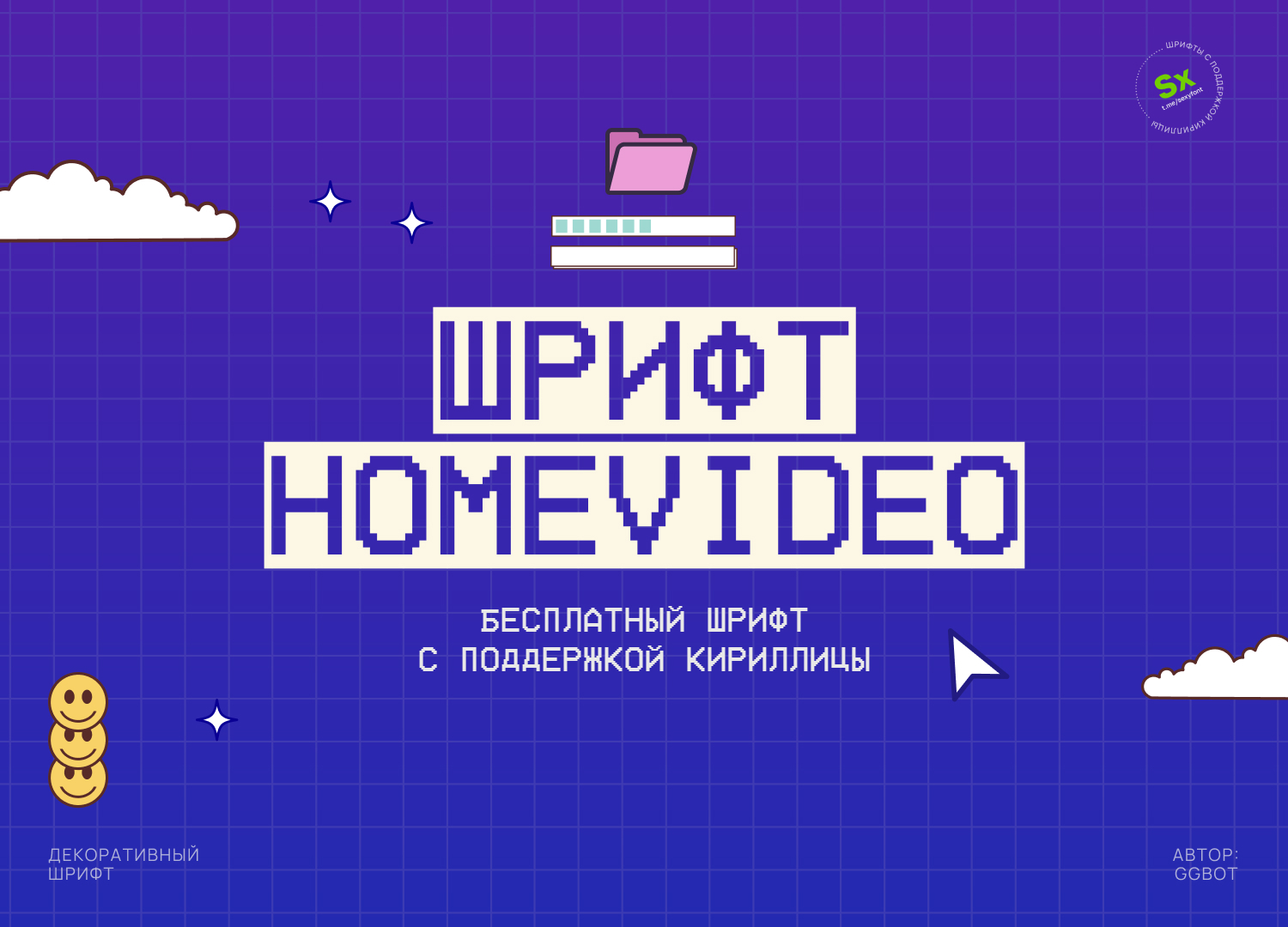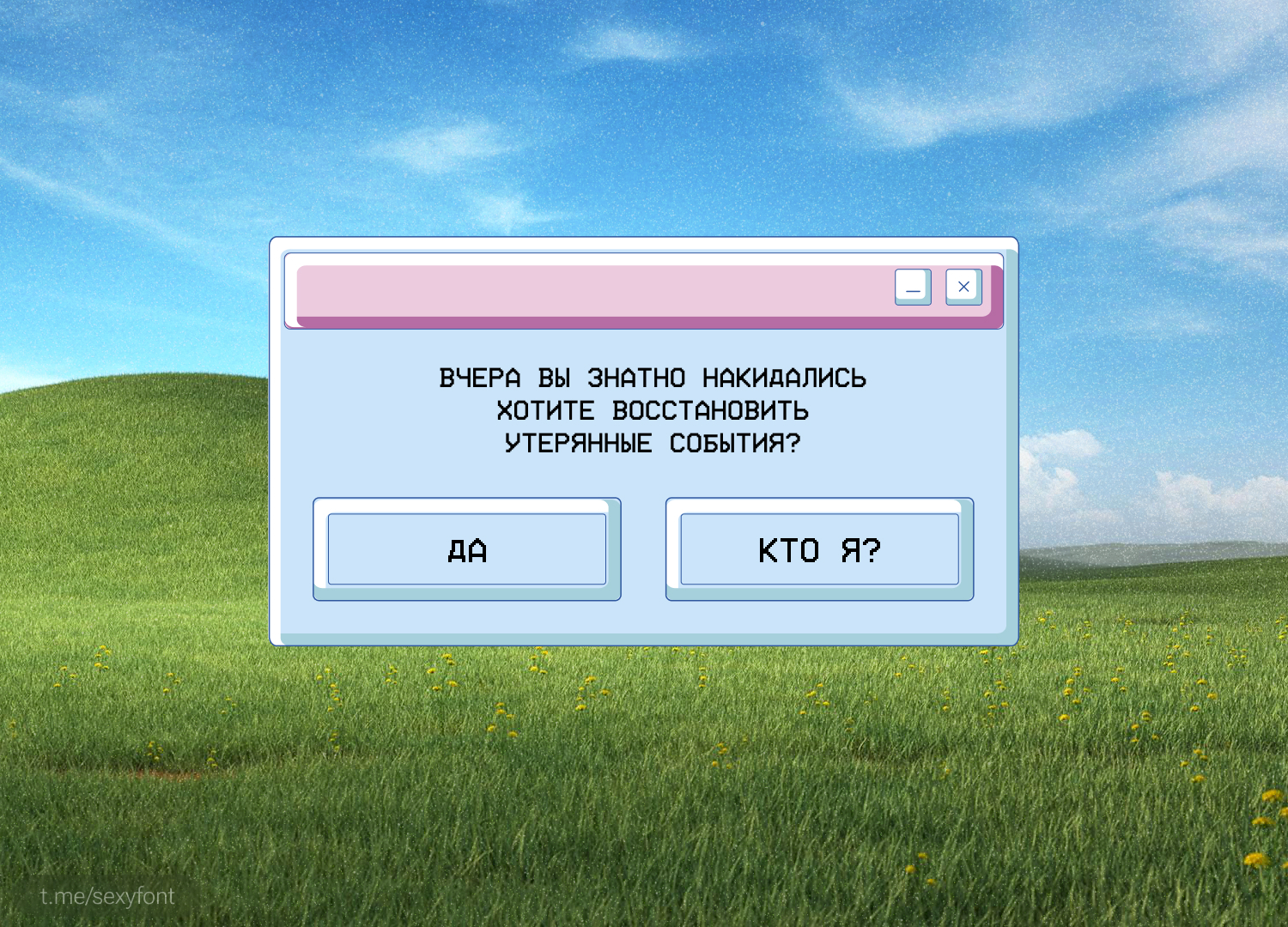
Homevideo. Пиксельный шрифт со странным названием) Что-то со временем старых операционок или приставки денди.
В общем играйся) Только не долго! Кинескоп посадишь!